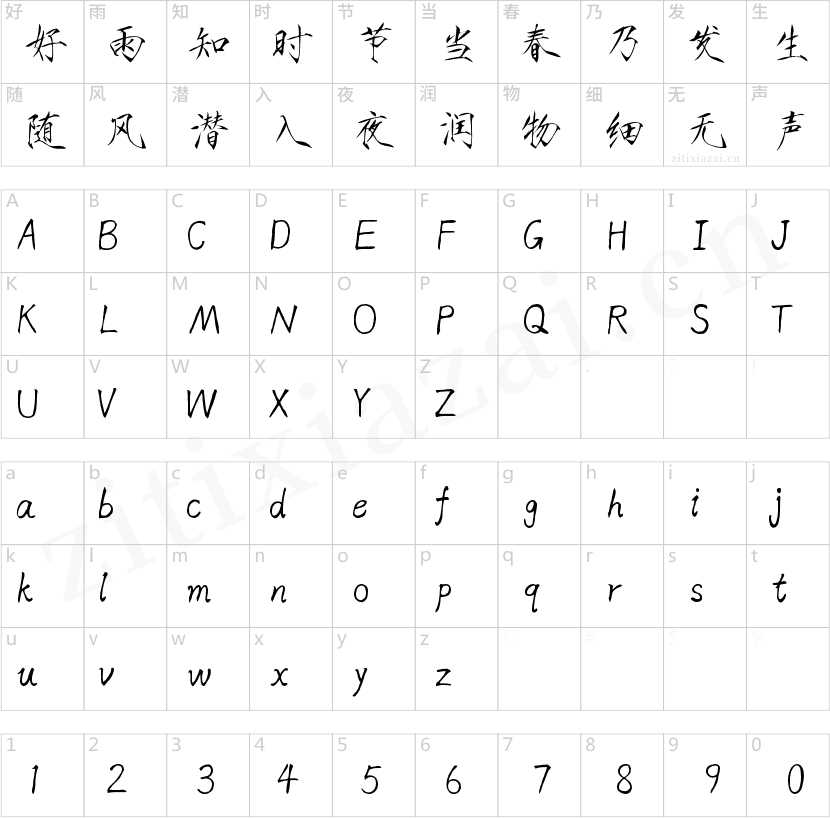
Aa瘦金体超大字库
Aa瘦金体超大字库,这款字体结构工整、笔画清晰,兼顾美观与易读性,适用于标题、正文、海报、包装、LOGO 等多种场景。字形优雅稳定,风格百搭耐看,适配日常排版与创意设计,让文字呈现更舒适、更具质感。Aa瘦金体超大字库一笔一画,皆是细节,以均衡的比例、流畅的线条打造舒适视觉体验,字形端正大气,风格简约现代。无论是商业设计、品牌宣传还是日常排版,都能轻松驾驭,让文字更有格调与力量。Aa瘦金体超大字库字体下载。
Aa瘦金体超大字库字体
Aa瘦金体超大字库是一款非常具有艺术性的字体,它的设计灵感来源于对古典艺术的研究,同时又融入了现代字体设计的元素。字形优美,笔画粗细变化自然,给人以大气、典雅的感觉。Aa瘦金体超大字库是一款既传统又现代的字体,它的设计充满艺术感,美观大方,实用性也非常强。无论是对于设计师还是对于普通读者来说,都是一种非常不错的字体选择。Aa瘦金体超大字库适合用于具有艺术感的场合,比如海报、宣传单张、书籍封面等。由于其字形流畅且具有动态感,也适合用于大量的文本排版,如报纸、杂志等。
Aa瘦金体超大字库